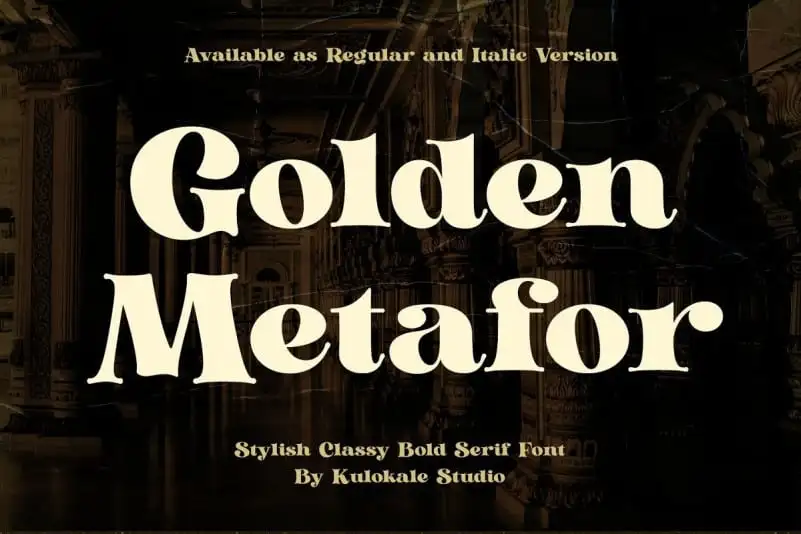
A Golden Metafor Serif Font é uma excelente escolha para quem busca uma fonte serif que expressa a sofisticação do design tipográfico de moda dos anos 80 até hoje. Esta fonte destaca-se por suas curvas elaboradas e formas únicas, tornando-a perfeita para aplicações em cabeçalhos e logotipos. O designer Kulokale criou essa elegante serif bold com caracteres atraentes e também ligaturas que facilitam o processo de criação de um bom logotipo tanto para seu próprio branding pessoal quanto para negócios. A Golden Metafor Serif é uma escolha ideal para qualquer projeto onde você precisa de fontes com estilo, modernidade e sofisticação para destacar sua marca ou mensagem.